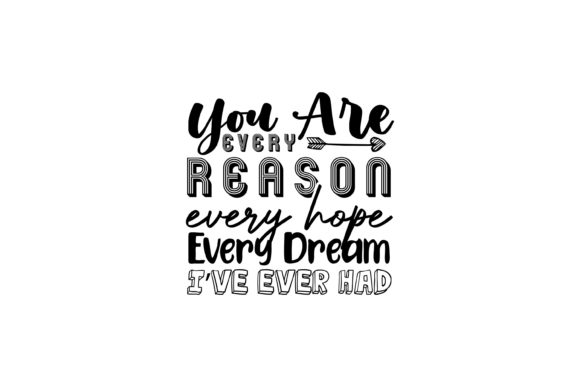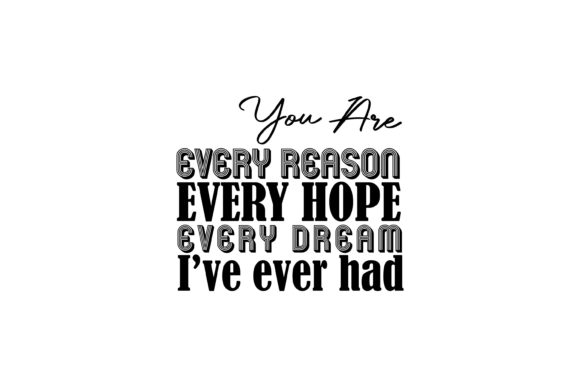
Every Dream-Love Quotes Font
Als u op zoek bent naar hoogwaardige middelen zoals Every Dream-Love Quotes Font, is dit premiumpakket een fantastische keuze voor uw creatieve projecten.